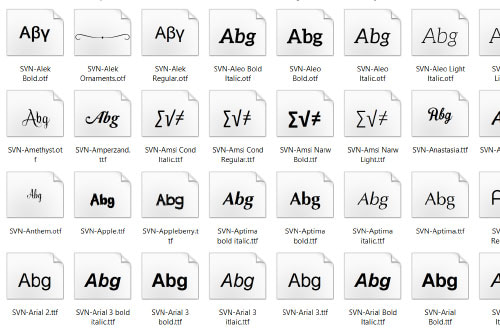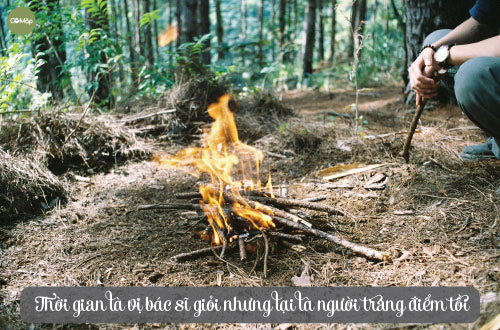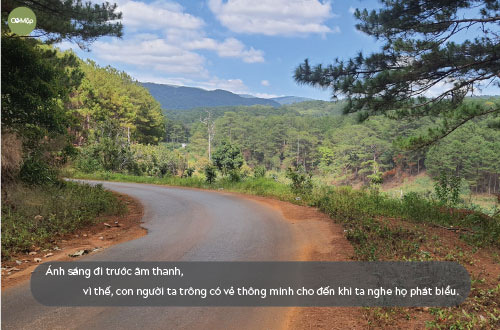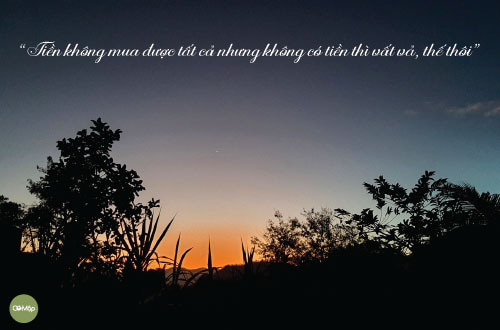
Font SVN - Thỏa sức sáng tạo với hơn 1.000 font chữ miễn phí
Font chữ là một trong những yếu tố quan trọng nhất trong thiết kế đồ họa. Một bộ font chữ đẹp, dễ đọc và phù hợp với nội dung sẽ giúp thiết kế của bạn trở nên chuyên nghiệp và thu hút hơn.
Trong bài viết này, chúng ta sẽ cùng tìm hiểu về bộ font chữ SVN - một bộ font chữ Việt hóa miễn phí, đa dạng phong cách.
Font SVN là gì?
Bộ font svn việt hóa đầy đủ
Font SVN là viết tắt của bộ font chữ Việt Nam, một bộ font chữ Việt hóa được phát triển bởi nhóm SVN Font. Bộ font này bao gồm nhiều font chữ với nhiều phong cách khác nhau, từ hiện đại đến cổ điển, từ thanh lịch đến mạnh mẽ.
Các font chữ SVN đều được thiết kế theo tiêu chuẩn Unicode, đảm bảo khả năng tương thích với tất cả các trình duyệt web và hệ điều hành.
Đặc điểm của font SVN
Font svn việt hóa thanh lịch, hiện đại
Các font chữ SVN có những đặc điểm nổi bật sau:
• Đa dạng phong cách: Các font chữ SVN có thể đáp ứng mọi nhu cầu thiết kế, từ thiết kế website, thiết kế đồ họa, đến thiết kế in ấn.
• Đẹp mắt, dễ đọc: Các font chữ SVN được thiết kế với đường nét tinh tế, rõ ràng, giúp người dùng dễ dàng đọc và hiểu nội dung.
• Tương thích cao: Các font chữ SVN đều được thiết kế theo tiêu chuẩn Unicode, đảm bảo khả năng tương thích với tất cả các trình duyệt web và hệ điều hành.
Các font chữ SVN phổ biến
Font svn việt hóa sang trọng, hiện đại
• SVN-Avo: Font chữ sans-serif hiện đại, thanh lịch, phù hợp cho các thiết kế website, logo, poster,...
• SVN-Traijan Pro: Font chữ sans-serif mạnh mẽ, cá tính, phù hợp cho các thiết kế website, đồ họa,...
• SVN-Avenida: Font chữ sans-serif cổ điển, sang trọng, phù hợp cho các thiết kế website, in ấn,...
• SVN-Mabella: Font chữ script thanh lịch, lãng mạn, phù hợp cho các thiết kế website, đồ họa,...
• SVN-Bellwethers: Font chữ viết tay mang phong cách lãng mạn, phù hợp cho các thiết kế văn học, nghệ thuật.
• SVN-TheUntold Story: Font chữ viết tay mang phong cách vui nhộn, tinh nghịch, phù hợp cho các thiết kế đồ họa, website,...
• SVN-The Carpenter: Font chữ viết tay mang phong cách cổ điển, sang trọng, phù hợp cho các thiết kế logo, wedding,...
• SVN-Gilroy: Font chữ sans-serif hiện đại, thanh lịch, phù hợp cho các thiết kế website, logo, poster,...
• SVN-Gotham: Font chữ sans-serif hiện đại, mạnh mẽ, phù hợp cho các thiết kế website, đồ họa,...
Cách sử dụng font SVN
Font svn việt hóa với đầy đủ phong cách
Khi sử dụng font SVN, bạn cần lưu ý một số điều sau:
• Sử dụng font chữ phù hợp với nội dung: Bạn nên chọn font chữ phù hợp với nội dung và phong cách thiết kế. Ví dụ, nếu thiết kế của bạn có nội dung chuyên nghiệp, bạn nên sử dụng font chữ sans-serif. Nếu thiết kế của bạn có nội dung sáng tạo, bạn có thể sử dụng font chữ script hoặc font chữ brush.
• Sử dụng font chữ hợp lý: Bạn không nên sử dụng quá nhiều font chữ trên một trang thiết kế. Điều này sẽ khiến thiết kế của bạn trở nên rối mắt và khó đọc.
Kết luận
Font SVN là một bộ font chữ Việt hóa đẹp mắt, dễ đọc và đa dạng phong cách. Bộ font chữ này sẽ giúp thiết kế của bạn trở nên chuyên nghiệp và thu hút hơn.
Dưới đây là một số gợi ý về cách sử dụng font SVN:
• Sử dụng font SVN-Avo cho các tiêu đề và nội dung chính của thiết kế.
• Sử dụng font SVN-Traijan Pro cho các thành phần phụ và nội dung phụ của thiết kế.
• Sử dụng font SVN-Avenida cho các logo và thiết kế đồ họa.
• Sử dụng font SVN-Mabella cho các thiết kế văn học và nghệ thuật.
Bạn có thể kết hợp các font chữ SVN khác nhau để tạo ra những thiết kế độc đáo và ấn tượng.